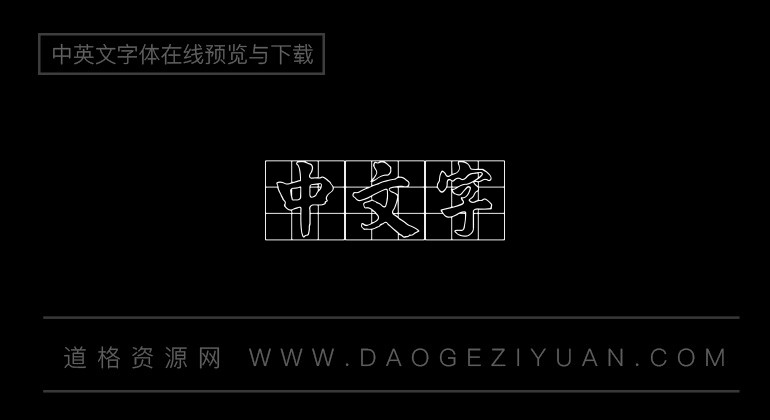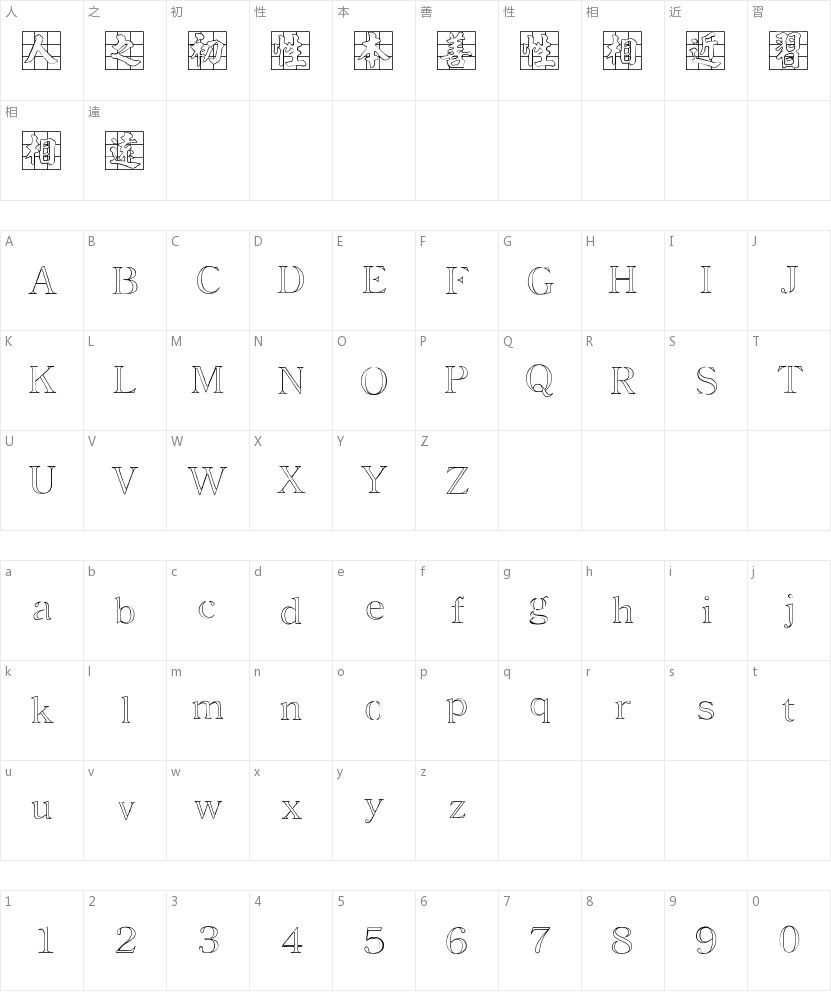
? 金梅楷书九宫空心字体是一种书法字体,它是由书法家王梅先生设计的。这种字体有九个宫格,空心字体更显精致,更适合书写。字体的笔画细腻,结构清晰,笔画的连接紧凑,更能体现出书法的美感。它的笔画流畅,结构紧凑,表达出时尚的风格,具有较强的装饰性。文件名:jinmeikaishujiugongkong.ttf
金梅楷书九宫空心是一款非常不错的手写艺术字体,具有很好的视觉感,适合于文化类的宣传设计、商业类品牌的广告和产品包装设计以及个性化文字排版等较多场景。